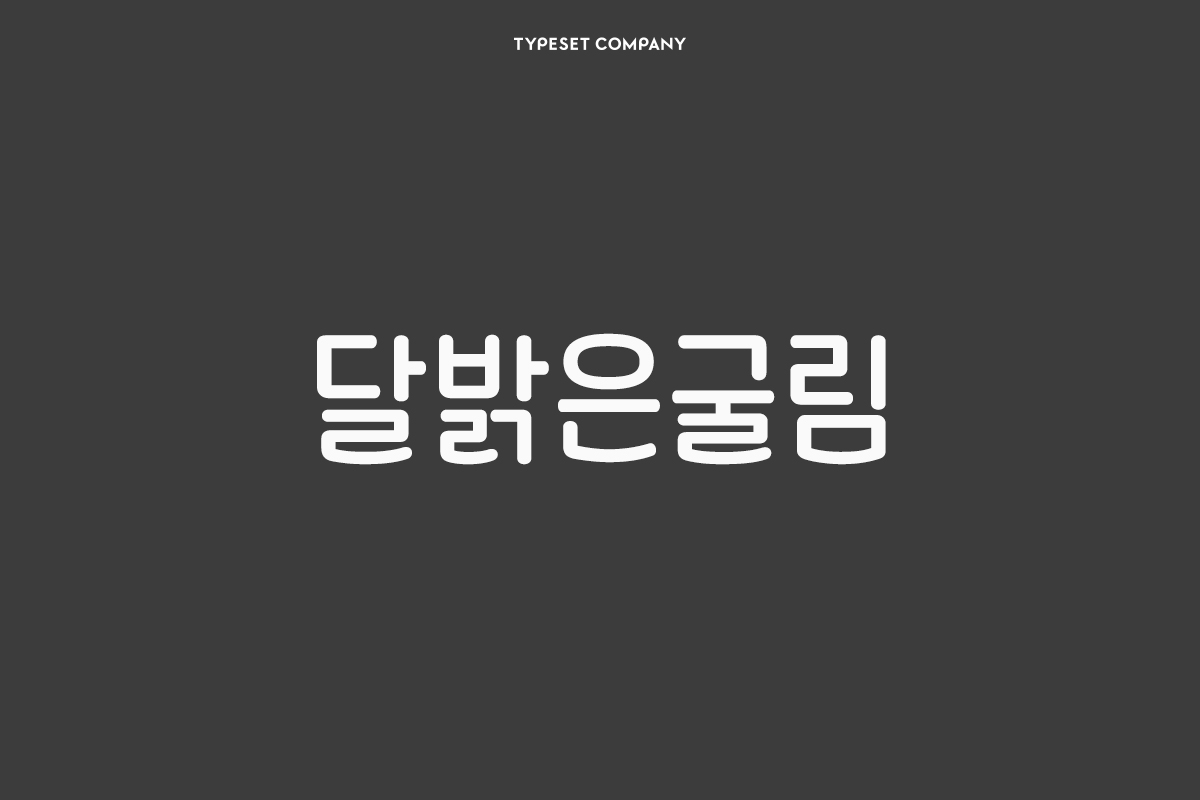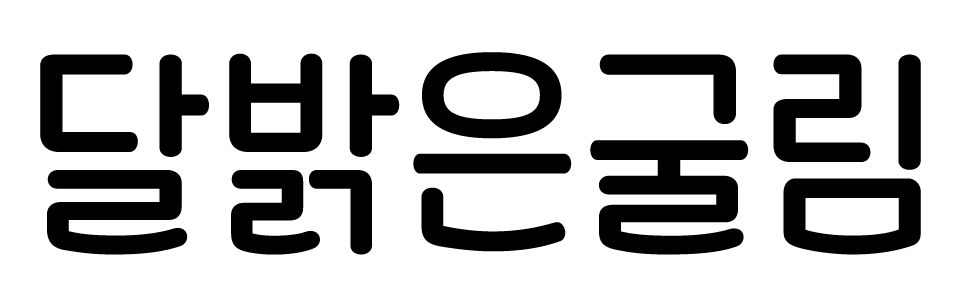
TSC달밝은굴림
귀여운제목용
TSC달밝은굴림 font in use
‘TSC 달밝은굴림’은 ‘TSC 해맑은굴림’을 더욱더 반듯하게 조정한 굴림 폰트다. 둥글게 마무리되는 아래 획들은 어두운 밤 환하게 웃고 있는 밝은 달을 닮았다.
• Serif,디스플레이
• TSC달밝은굴림 / TSCMoonytype